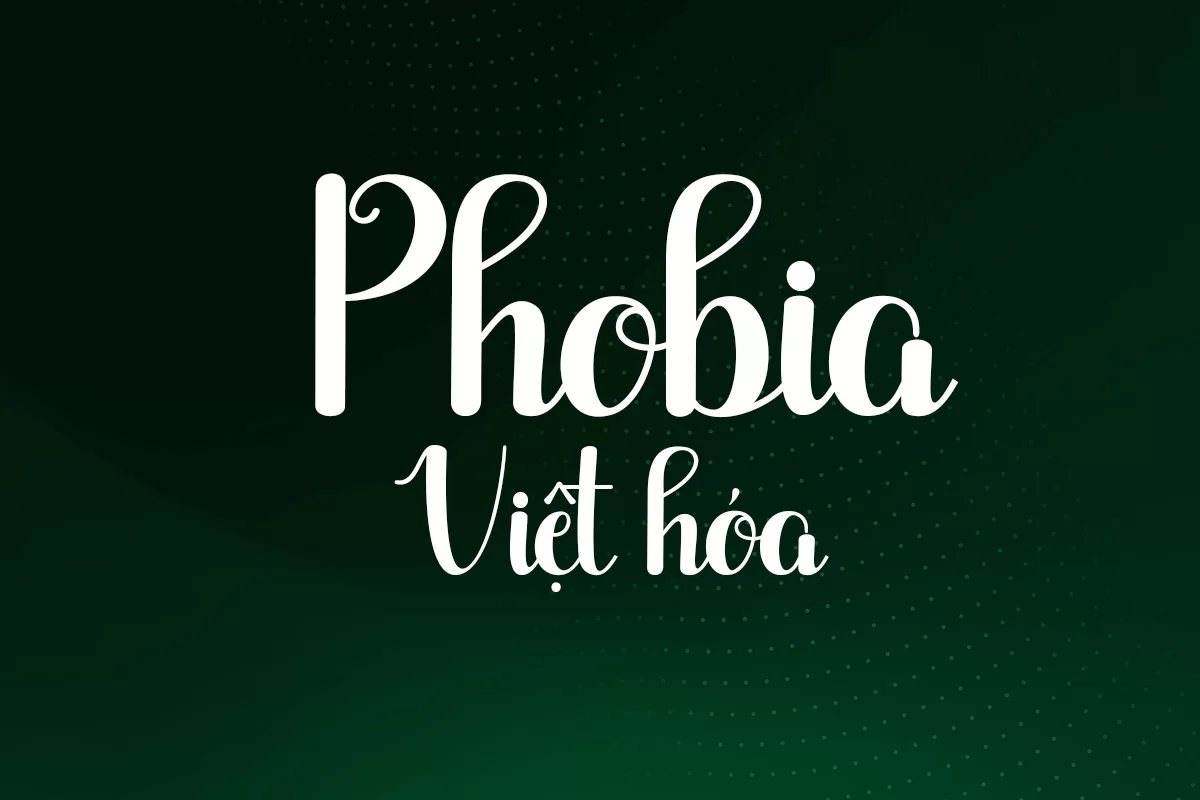
Phobia Việt hóa là một kiểu chữ viết tay hiện đại với đường nét uyển chuyển và mềm mại. Nét đặc trưng của font là các chữ cái cao vừa phải, bo tròn nhẹ ở đầu và cuối nét, tạo cảm giác nữ tính, thanh lịch nhưng không kém phần cá tính. Font đặc biệt phù hợp cho các thiết kế thiệp cưới, tiêu đề blog, bìa sách, hoặc các ấn phẩm thương hiệu hướng đến sự dịu dàng và tinh tế. Phiên bản Việt hóa được tối ưu hóa dấu tiếng Việt đầy đủ, giữ nguyên tinh thần nguyên bản nhưng vẫn dễ đọc và hài hòa với bảng chữ cái tiếng Việt. Nếu bạn đang tìm một font viết tay nhẹ nhàng mà vẫn có cá tính riêng, Phobia là lựa chọn đáng cân nhắc.